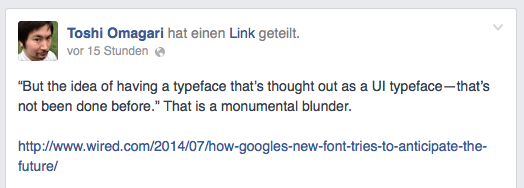
Artikel: Neue Google-Schrift Roboto
Eine Aussage im Artikel erscheint mir allerdings etwas verwegen:
the idea of having a typeface that’s thought out as a UI typeface—that’s not been done before
Was ist mit Erik Spiekermanns Schrift für Nokia? Was ist mit Ubuntu? Goggles eigener Droid-Familie? Und das sind doch nur die ersten Beispiele, die mein lahmes Hirn angeboten hat; es gibt sicherlich dutzende.